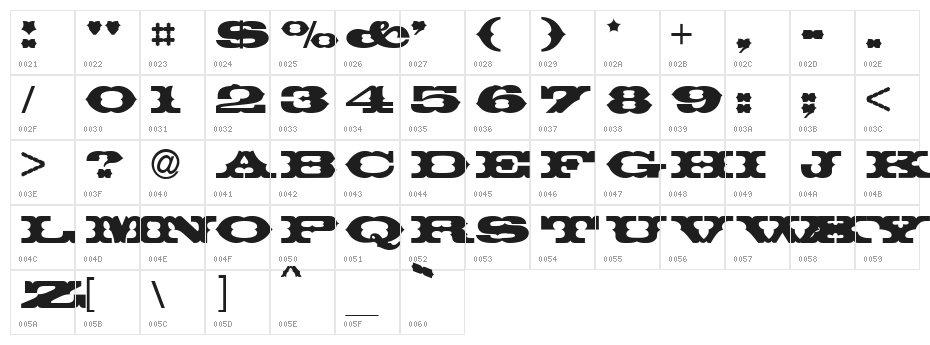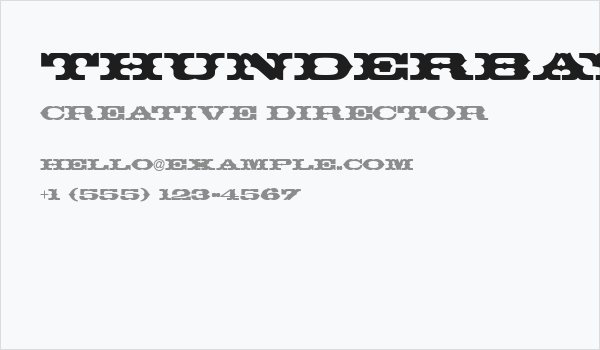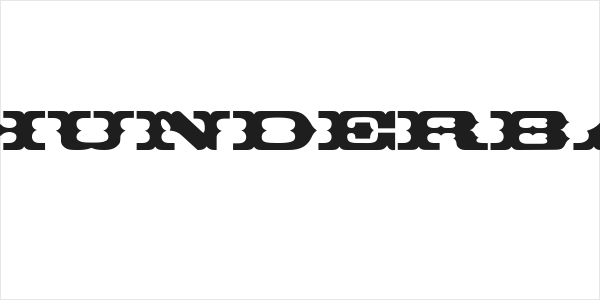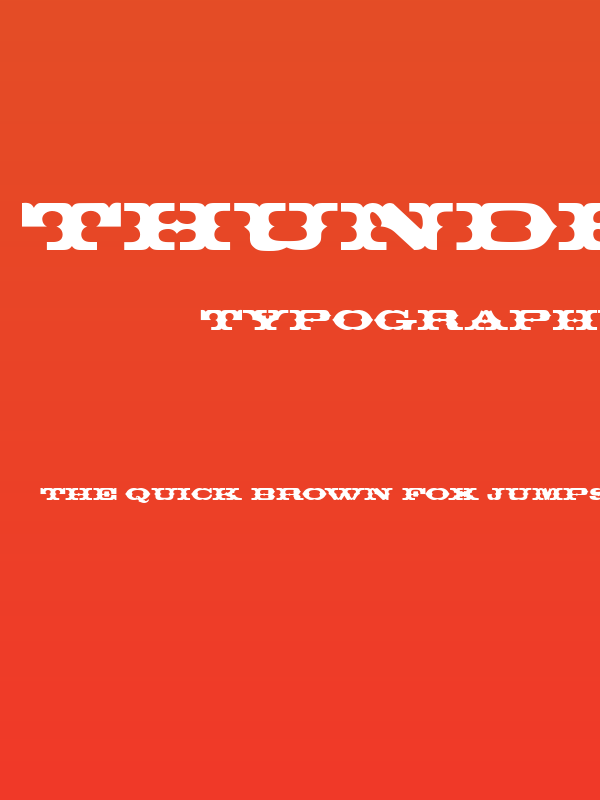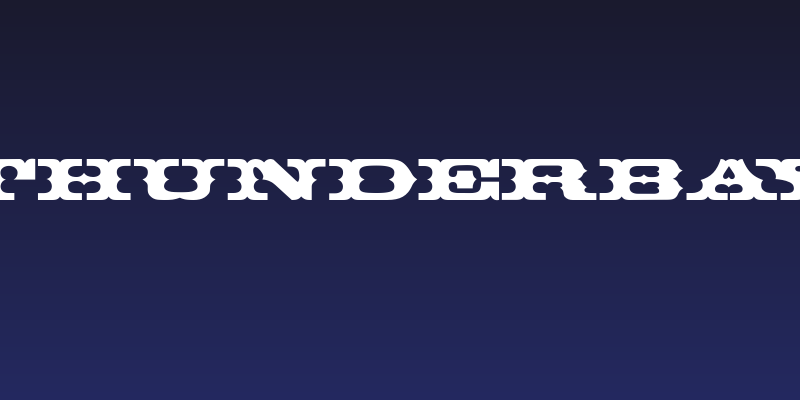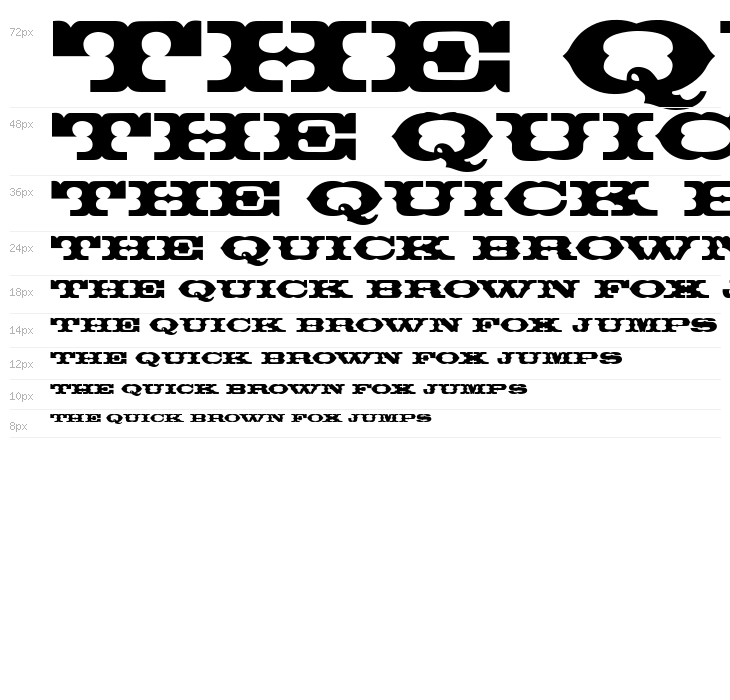
ThunderBay Font
✎ Western
| Gesamtstil | Vintage, Decorative |
| Vorgeschlagene Projekte | Ideal for posters, logos, branding, and any design work that requires a bold, decorative typeface with a vintage flair. |